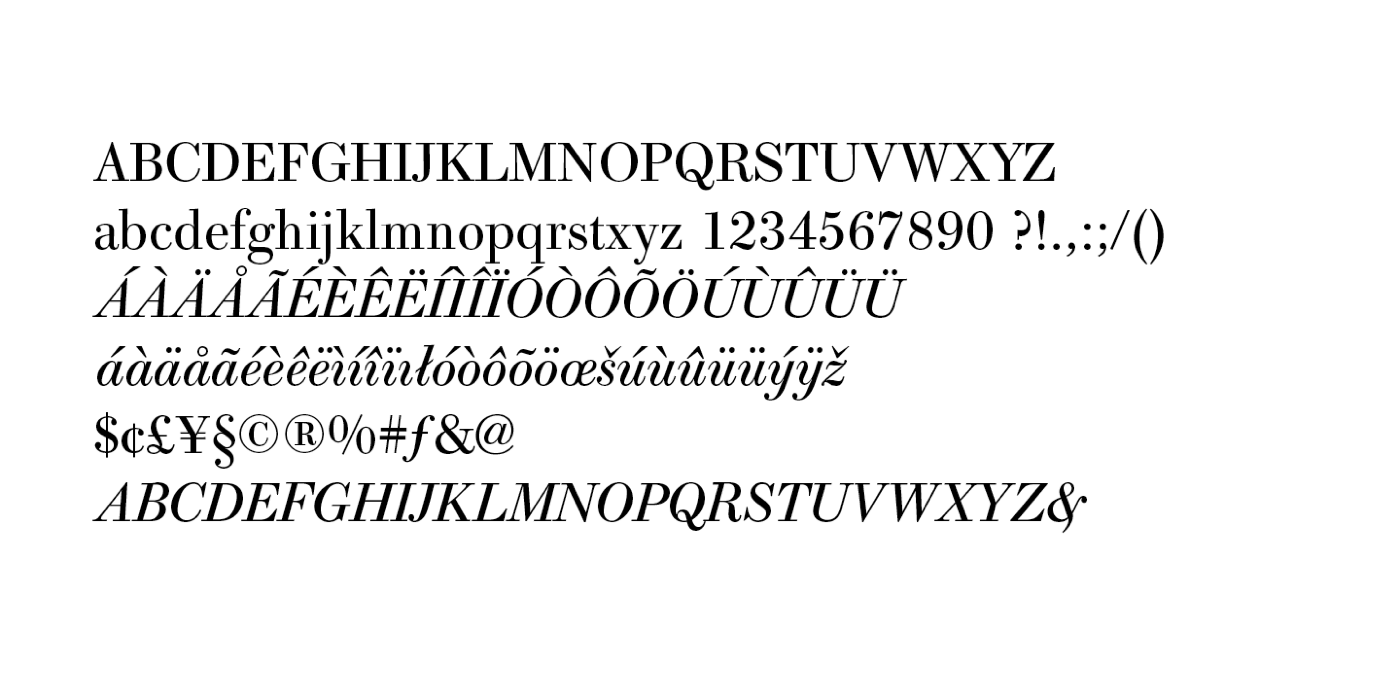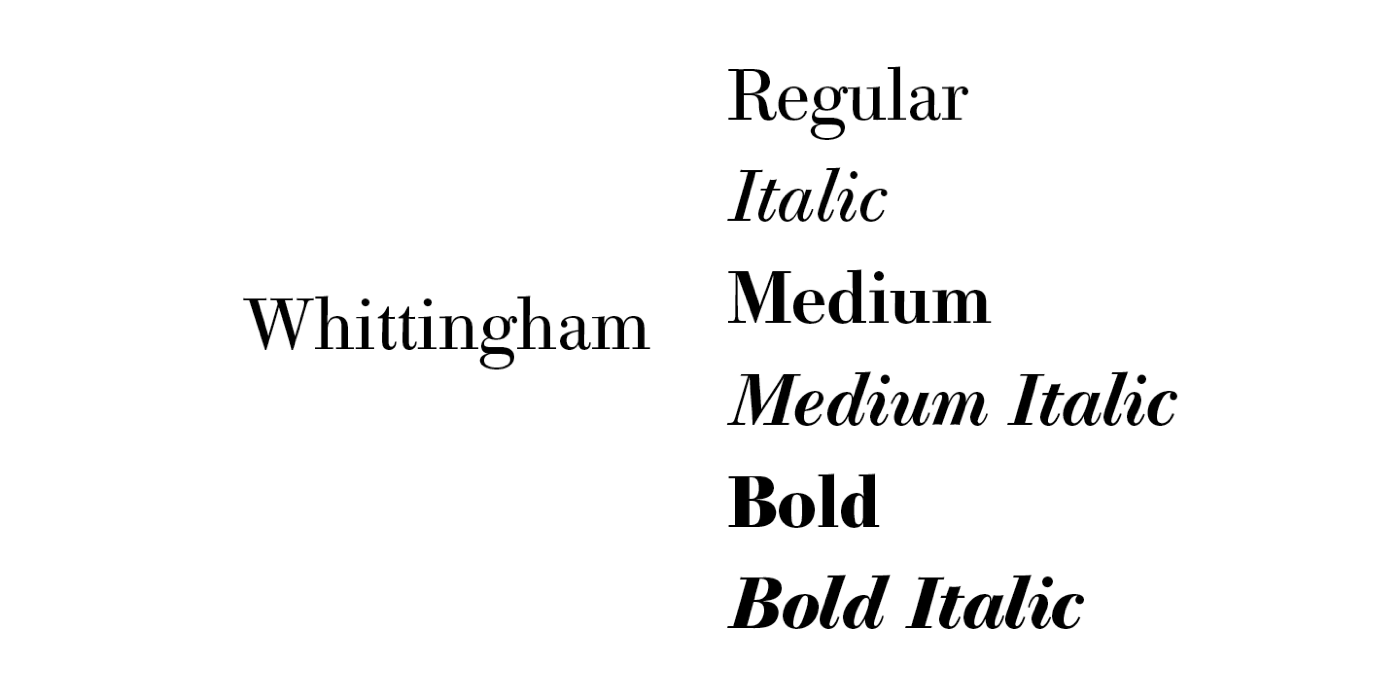
Die Whittingham ist eine klassizistische Antiqua von Günther Gerhard Lange und Dieter Hofrichter. Sie geht auf Schriften zurück, die um 1840 von Charles Whittingham bei der Chiswick Press in Birmingham eingesetzt wurden. Die Familie verfügt über drei Strichstärken mit Kursiven und Kapitälchen.